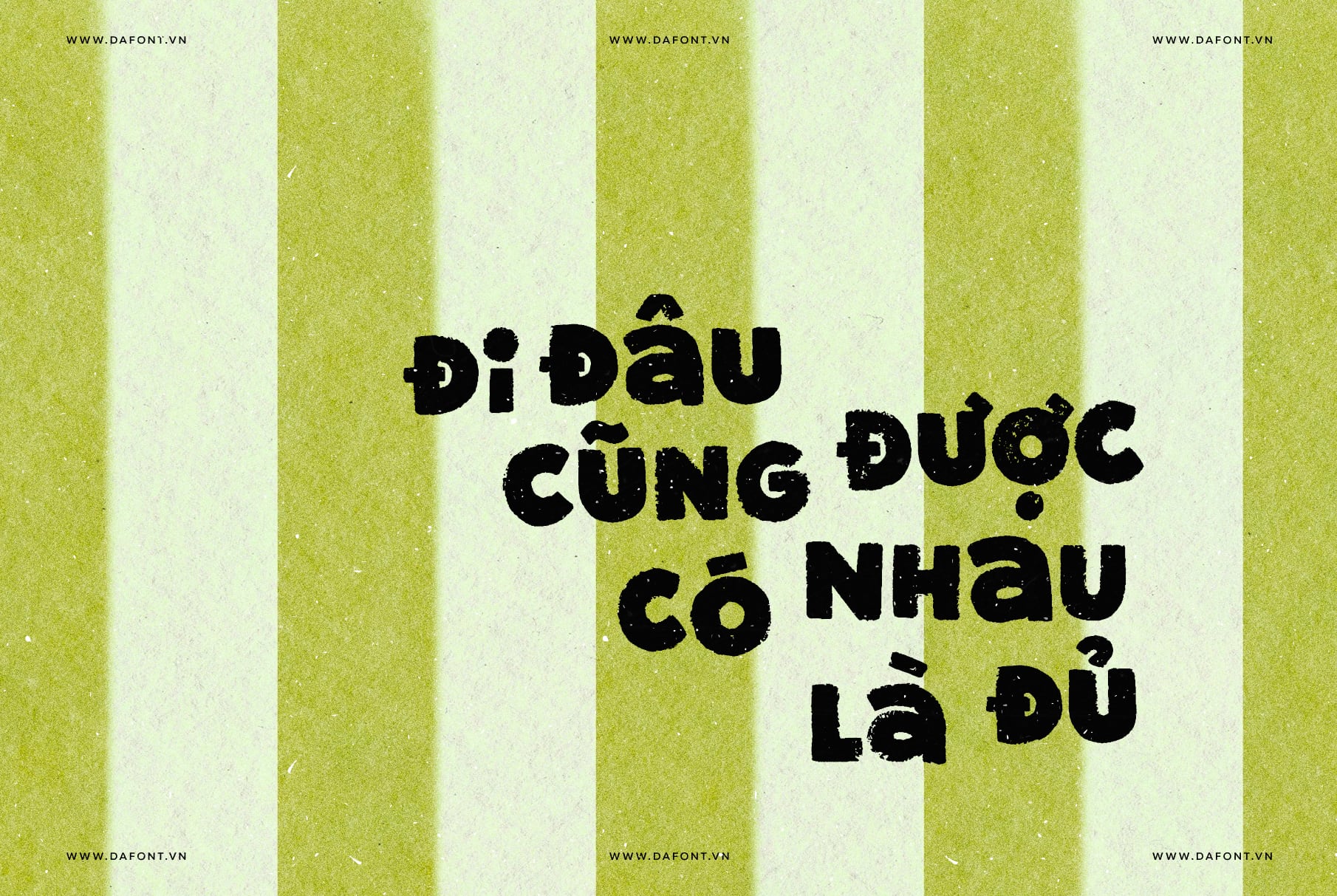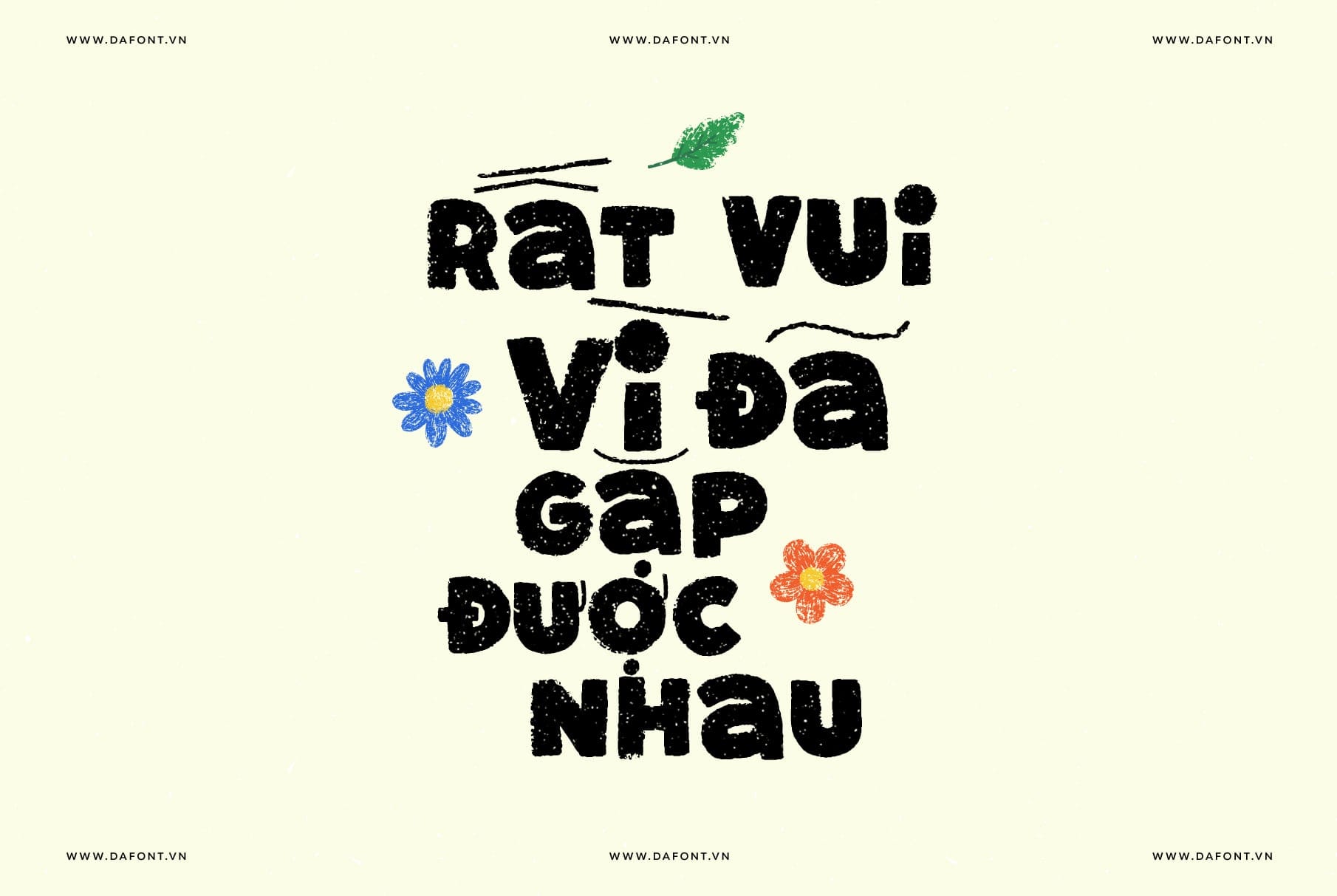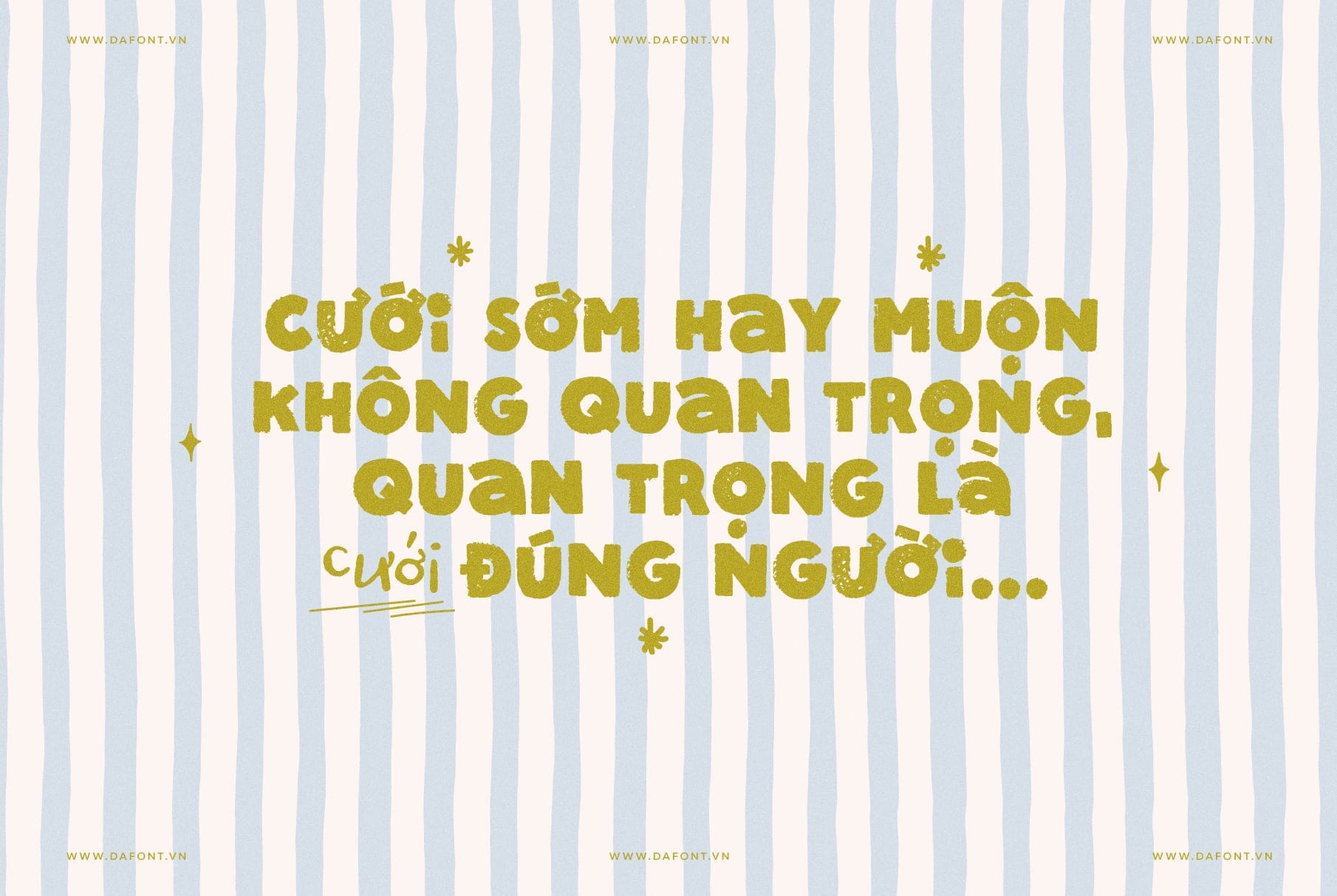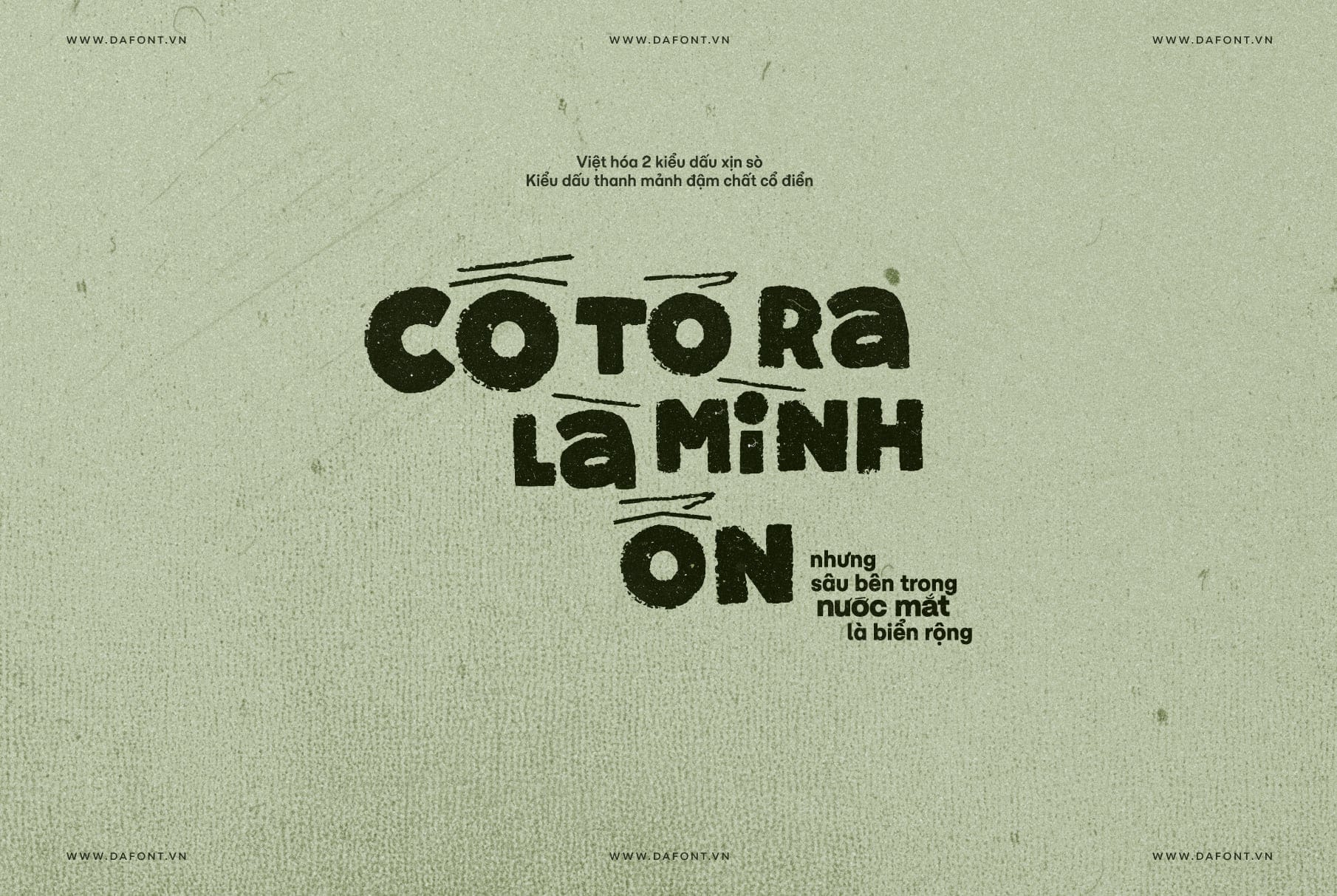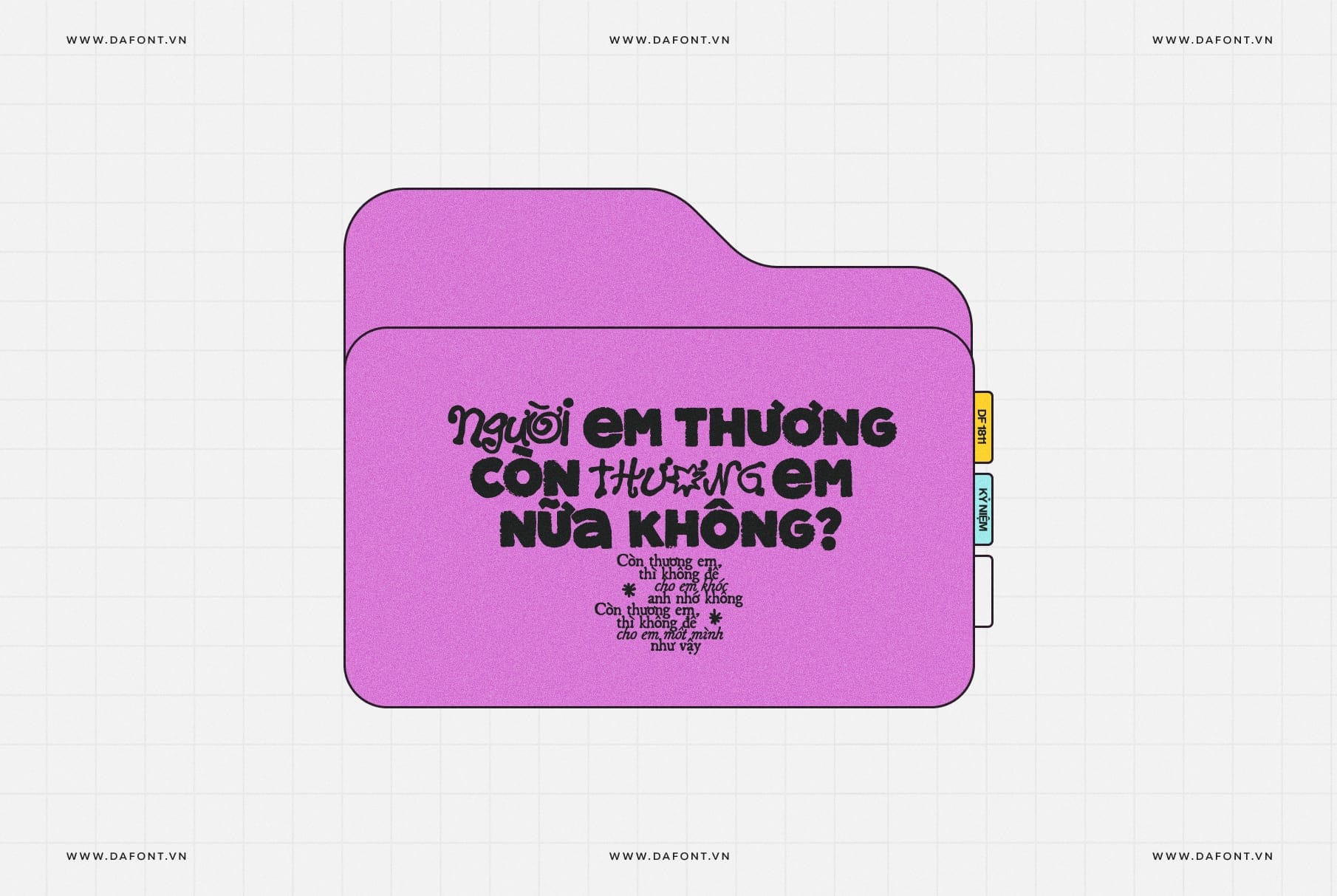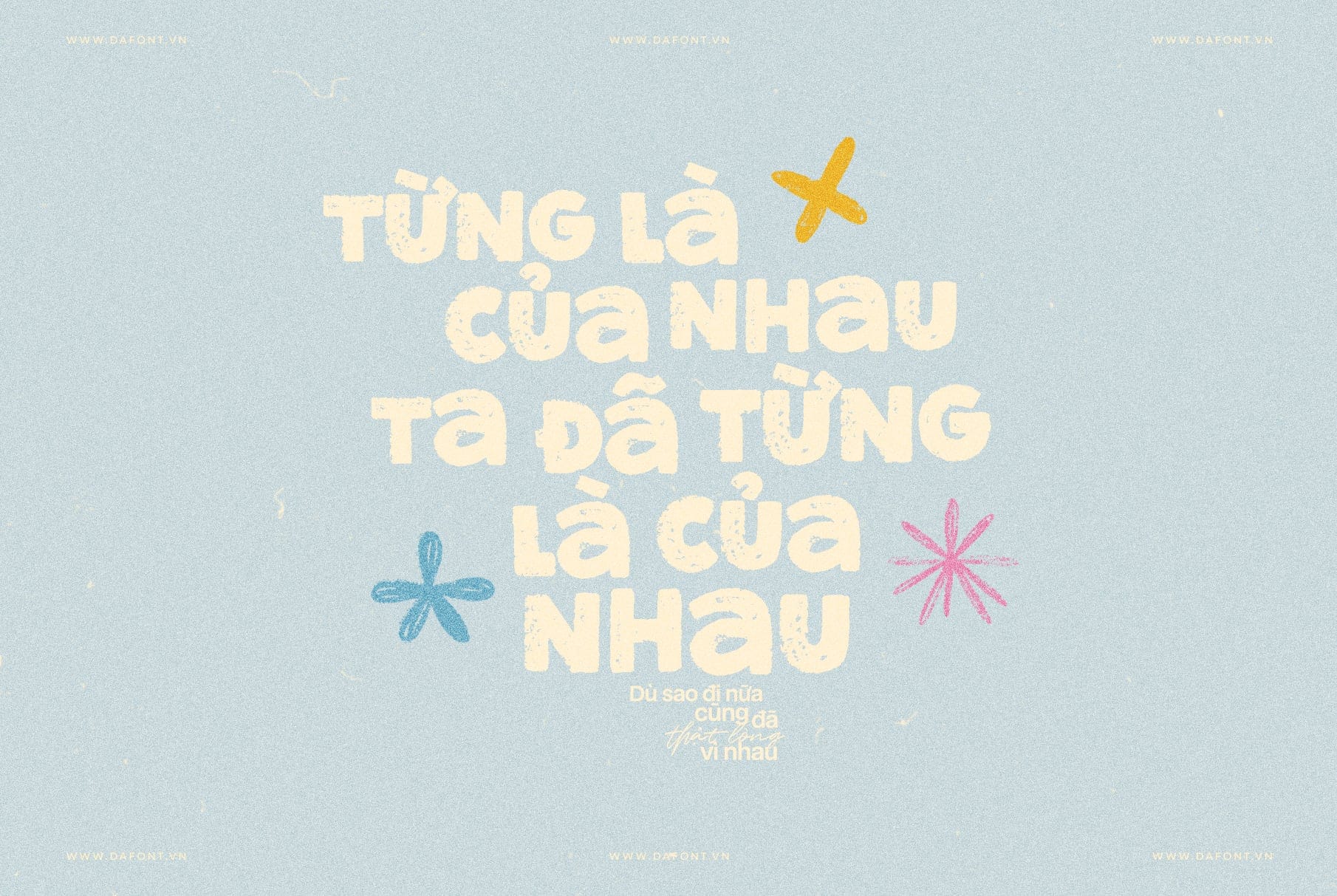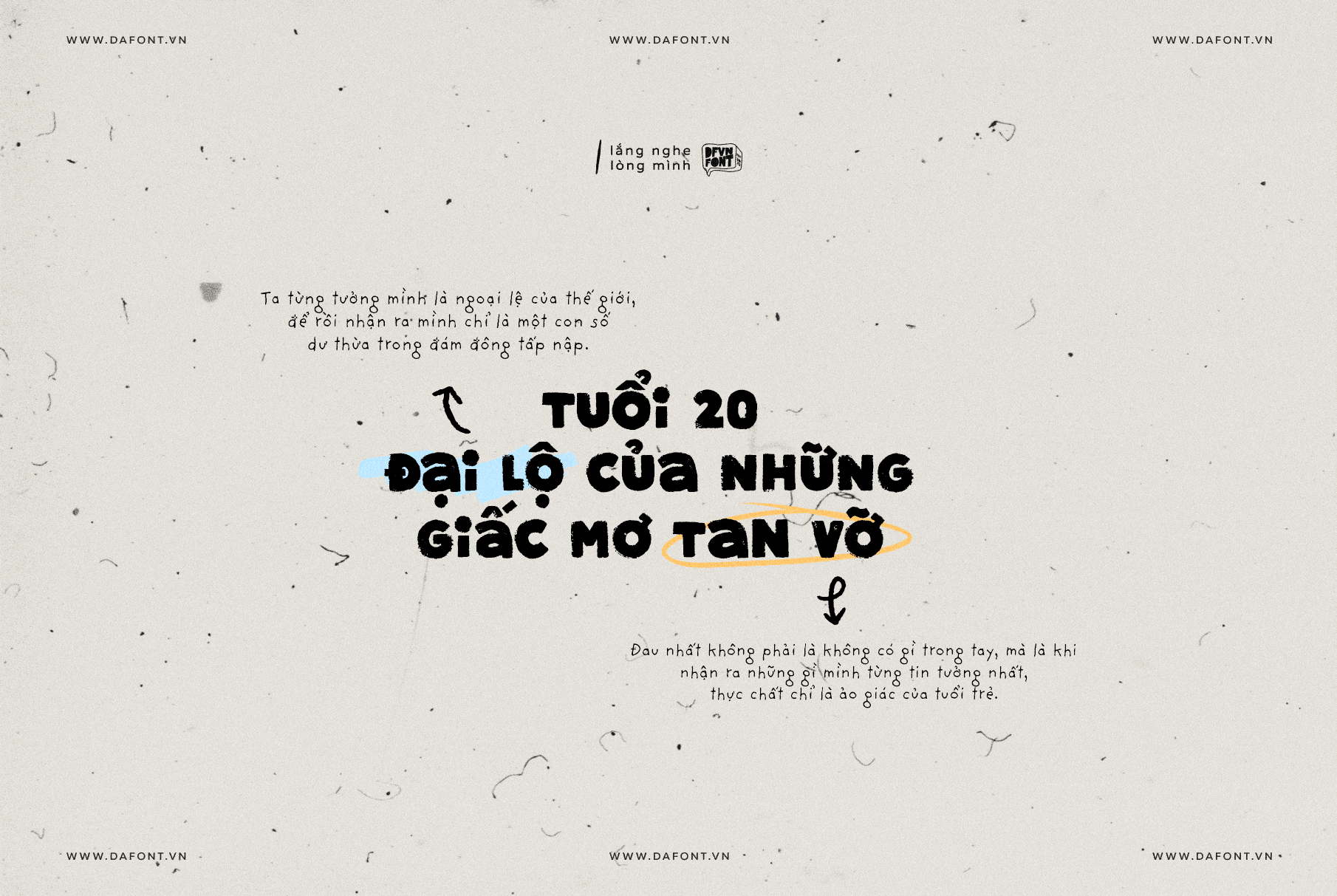
DFVN Super Curious font Việt hóa là display font, tức là font thiên về khả năng tạo ấn tượng mạnh ở phần tiêu đề, headline hoặc các mảng nội dung ngắn. Đây không phải kiểu font sinh ra để dàn những đoạn văn dài, mà phù hợp hơn với các vị trí cần thu hút ánh nhìn ngay từ lần đầu tiên.
Điểm dễ nhận ra của font là bề mặt chữ có cảm giác textured, hơi thô nhẹ, mang tinh thần thủ công và retro. Chính điều này giúp DFVN Super Curious Việt hóa trở nên nổi bật hơn, đồng thời tạo cảm giác mới mẻ và giàu cá tính trong các thiết kế hiển thị. Khi đặt trong các thiết kế mang tinh thần sáng tạo, lifestyle, vintage hoặc playful branding, font có khả năng tạo cảm xúc rất tốt.
Đặc điểm nổi bật của DFVN Super Curious
DFVN Super Curious gây ấn tượng mạnh ngay từ cái nhìn đầu tiên nhờ nét chữ đậm, cá tính và có chiều sâu thị giác. Thay vì các đường nét sắc, trơn mịn như đa số font thời kỹ thuật số, mỗi ký tự của Super Curious sở hữu độ nhám, vết xước và sự không đều có chủ ý, tạo cảm giác “handmade” rất chân thật.
- Phong cách texture retro, bề mặt chữ như được in bằng khuôn gỗ hoặc mực trên giấy đã cũ.
- Dáng chữ unicase (chữ cái đồng nhất kiểu viết tay) mang lại sự phóng khoáng, tự do, phù hợp các layout sáng tạo.
- Mỗi ký tự có cá tính riêng, không quá đều đặn, giúp tổng thể thiết kế trở nên nhớ lâu và khác biệt.
- Đi kèm alternate và ligature, giúp sắp chữ linh hoạt, tự nhiên hơn, tránh cảm giác lặp lại nhàm chán.
Nhờ những yếu tố này, DFVN Super Curious không phù hợp cho nội dung dài mà sinh ra để làm tiêu đề, logo và các điểm nhấn cần thu hút ánh nhìn ngay lập tức.
DFVN Super Curious phù hợp dùng trong những thiết kế nào?
Super Curious được xếp vào nhóm display font, nghĩa là rất mạnh về mặt nhận diện và không phù hợp dùng cho đoạn văn bản dài. Thay vào đó, font này phát huy tối đa sức mạnh khi đảm nhận vai trò tiêu đề, chữ chính hoặc điểm nhấn.
Một số trường hợp sử dụng lý tưởng:
- Logo thương hiệu cá tính, mang tinh thần thủ công, vintage hoặc creative.
- Poster sự kiện, festival, workshop, minigame cần gây chú ý mạnh từ xa.
- Bìa sách, bìa tạp chí, cover album theo phong cách hoài cổ hoặc indie.
- Thiết kế sticker, quote art, thumbnail mạng xã hội (Facebook, Instagram, TikTok) với thông điệp ngắn, đậm chất cá nhân.
- Bao bì sản phẩm thủ công, đồ ăn, đồ uống, coffee shop, đồ trang trí, concept DIY.
Để font Super Curious phát huy tối đa sức mạnh, bạn cần lưu ý cách pairing với các font khác cũng như bối cảnh sử dụng.
Một số gợi ý:
- Dùng Super Curious cho tiêu đề, logo hoặc chữ chính, kết hợp với một font sans-serif đơn giản (như kiểu không chân, nét đều) cho nội dung phụ.
- Tránh sử dụng font này cho đoạn text dài vì texture và độ đậm sẽ gây mỏi mắt, giảm trải nghiệm đọc.
- Tận dụng alternate và ligature để các chữ không bị lặp form, giúp layout tự nhiên và đậm chất “hand-lettering” hơn.
- Khi thiết kế theo phong cách retro, hãy kết hợp với background màu trầm, hơi ngả vàng, chất liệu giấy cũ, grain hoặc hiệu ứng in lệch để “match” tinh thần font.
- Nếu thiết kế thương hiệu cao cấp nhưng vẫn muốn chút phá cách, có thể dùng Super Curious trong các ấn phẩm phụ (poster, social, bao bì limited) thay vì logo chính.
Bản Việt hóa độc đáo
Font được Việt hóa hoàn chỉnh, kerning đầy đủ toàn bộ ký tự giữ nguyên tinh thần bản font gốc. Toàn bộ các ký tự thay thế cũng được Việt hóa giúp thiết kế giàu nhịp điệu và cảm xúc hơn.
Điểm đặc biệt là bản Việt đi kèm 2 kiểu dấu riêng biệt:
- Kiểu dấu đậm, cá tính, mang đậm chất đặc trưng của font, phù hợp các thiết kế cần ấn tượng mạnh.
- Kiểu dấu thanh mảnh, mang hơi hướng cổ điển, phù hợp phong cách vintage nhẹ nhàng.
Bạn có thể dễ dàng chuyển đổi giữa các kiểu dấu bằng tính năng OpenType trong các phần mềm như Illustrator, Photoshop, giúp kiểm soát tone cảm xúc của thiết kế rất linh hoạt.
Kết luận
DFVN Super Curious Việt hóa không chỉ gây ấn tượng bởi phong cách retro textured đầy cá tính mà còn là một lựa chọn rất thực dụng cho các dự án thiết kế hiện đại cần dấu ấn thủ công và chiều sâu thị giác. Với các ký tự thay thế xịn sò, dấu tiếng Việt linh hoạt và khả năng ứng dụng tốt trong logo, poster, social graphic hay branding, đây là font rất đáng cân nhắc nếu bạn muốn thiết kế của mình bớt an toàn và nổi bật hơn ngay từ cái nhìn đầu tiên.